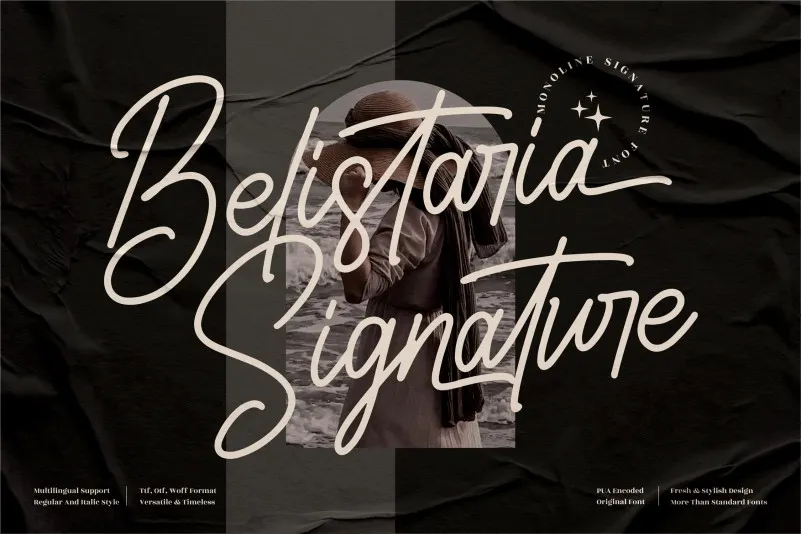
Belistaria Signature Font – Fonte Grátis
Belistaria Signature Font
A fonte ‘Belistaria Signature Font’ é uma escolha perfeita para qualquer projeto que busque agregar um toque de elegância a seu trabalho. Seja criando identidade visual para sua marca, desenhando produtos personalizados ou até mesmo produzindo designs de arte digital, esta fonte oferece um sabor premium ao seu trabalho. A ‘Belistaria Signature Font’ foi projetada especificamente para complementar suas criações com uma linguagem sofisticada e autêntica. É perfeita para aplicações como logotipos, embalagens de produtos, mugs personalizados, cartões de presentes, tags, e até mesmo sua foto nas redes sociais ou até mesmo nos seus trabalhos impressos. Seja qual for o seu projeto, esta fonte vai ajudá-lo a dar um passo a mais em suas criações digitais, oferecendo um tom elegante e sofisticado.